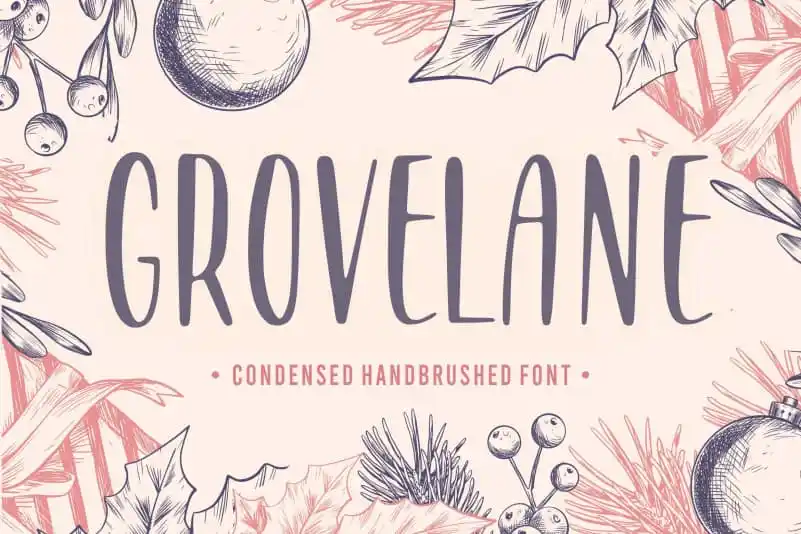
GROVELANE Handbrushed Font – Download Grátis
GROVELANE Handbrushed Font é uma elegante escolha para quem busca uma mistura única entre tipografia geométrica e estilo artesanal. Com seu design minimalista e sua superfície suavemente antiga, essa fonte traz um ar de sofisticação à qualquer projeto. Perfeita para aplicação em embalagens de produtos, identidades corporativas, revistas, redes sociais ou até mesmo para destacar mensagens sobre o fundo da página em projetos de casamento. Além de ser uma excelente opção para expressar palavras em destaque em ambientes mais elegantes, GROVELANE também é versátil e capaz de dar um toque autêntico a qualquer projeto visual. Para os amantes do design gráfico, essa fonte oferece o que há de melhor no mundo dos brushes digitais. Balpirick, designer responsável por esta incrível fonte, proporciona uma experiência de uso única, permitindo que os criativos maximizem seus recursos visuais com a facilidade e sofisticação de GROVELANE. Seja você um estilista de moda, um editor gráfico ou até mesmo alguém que quer dar um toque especial aos projetos do seu diário pessoal, GROVELANE é a escolha perfeita para trazer uma pitada de personalidade e charme ao seu trabalho.